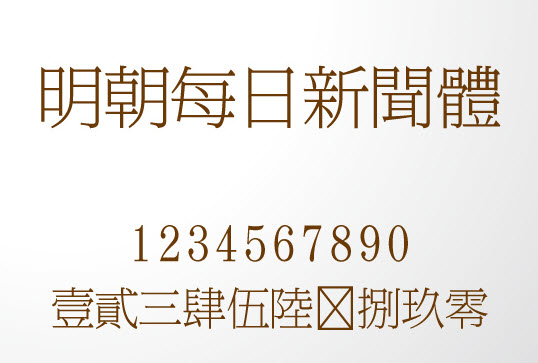
新聞明朝體是一款好用的繁體字體,字體非常的工整,筆畫纖細(xì),非常的秀氣,與一般報(bào)紙雜志的字體比較類似,歡迎喜愛的朋友到綠色資源網(wǎng)下載體驗(yàn)!
新聞明朝體是指宋體字在日本的稱呼,在臺(tái)灣和韓國(guó)也有明朝體的叫法。漢字的計(jì)算機(jī)Font技術(shù)最初由日本開發(fā),傳至臺(tái)灣,臺(tái)灣沿用了日本明朝體的稱呼。
《每日新聞》是日本非常普遍的一份報(bào)紙,也是日本歷史最悠久的報(bào)紙,每日新聞明朝體時(shí)一款非常適合做標(biāo)題的字體,字體結(jié)構(gòu)非常不錯(cuò),用來設(shè)計(jì)LOGO字體也是不錯(cuò)